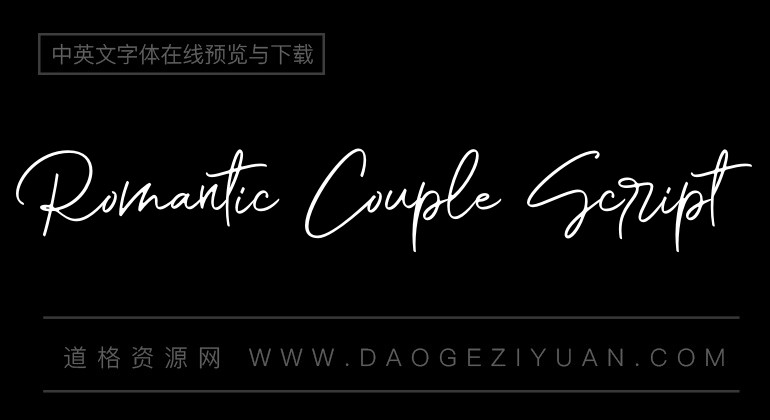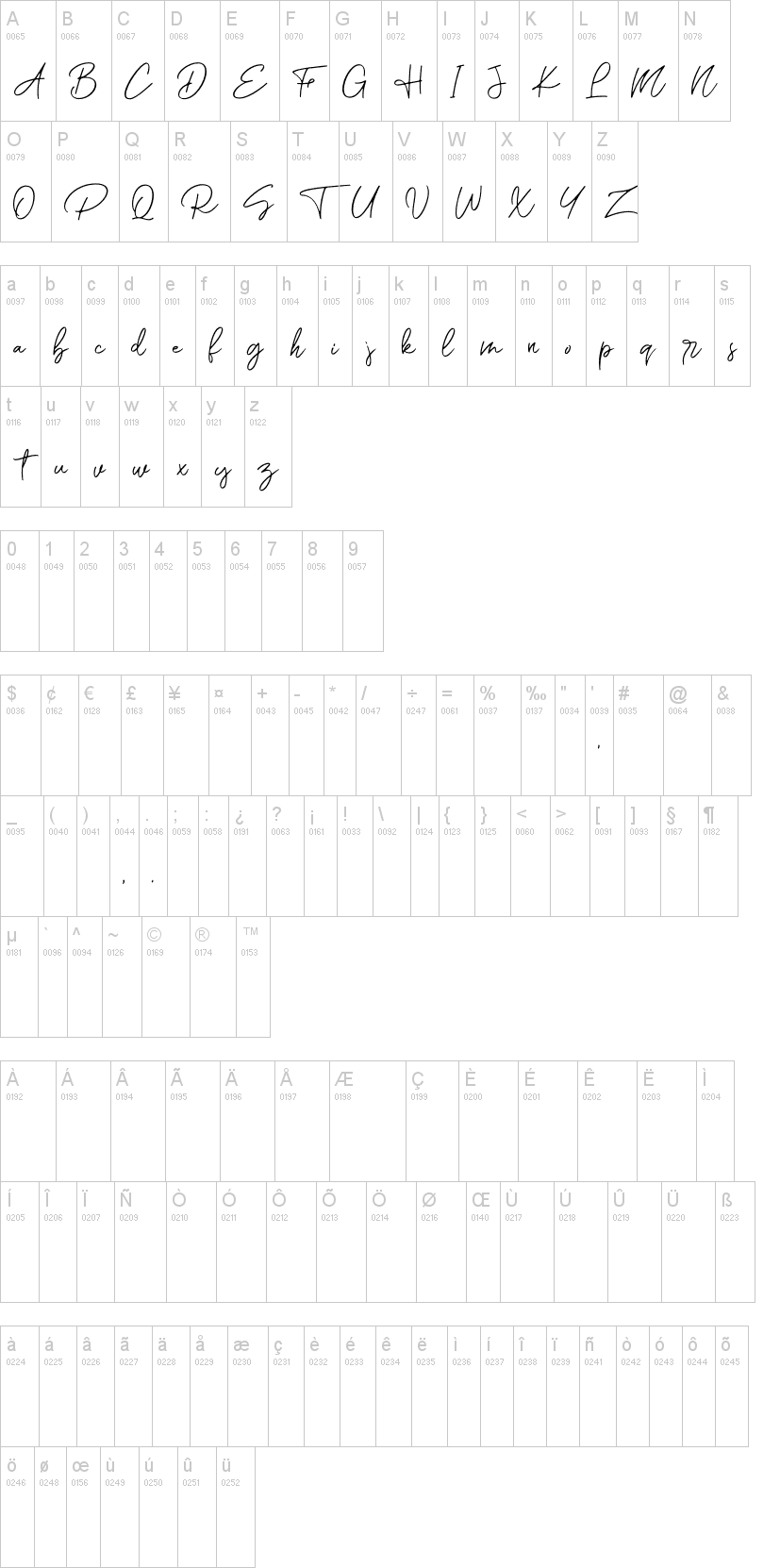
Romantic Couple Script
? Romantic Couple Script 字体是一种由美国设计师 Laura Worthington 创作的手写体字体,它具有浪漫、甜蜜、优雅的特点,可以用于各种浪漫的场景,如情人节、浪漫的约会、婚礼、情侣间的恋爱等。它的字形采用了细腻的折痕,可以表达出浪漫的情感,而且字体的细节也非常精美,可以帮助设计师创造出优雅的设计效果。
Romantic Couple Script是一款非常不错的手写艺术字体,具有很好的视觉感,适合于文化类的宣传设计、商业类品牌的广告和产品包装设计以及个性化文字排版等较多场景。
Romantic Couple Script字符映射图